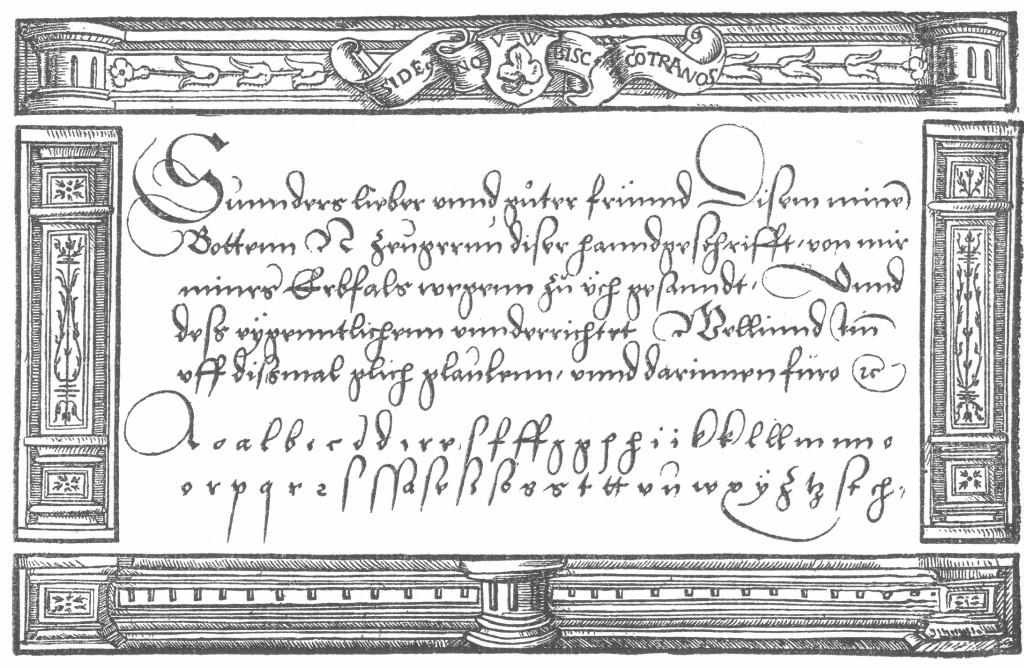
Grund für Blocksatz im Buchdruck
Ich wundere mich etwas, dass plötzlich pauschal über "alte Meister" und das Infragestellen (oder Nicht-Infragestellen) vermeintlich althergebrachter Regeln diskutiert wird. Ich habe nirgends die Forderung gelesen, den Blocksatz abzuschaffen, schon gar nicht vom Fragesteller, der ursprünglich nur wissen wollte, ob es  einen "historischen, technischen oder kaufmännischen Grund" für diese Tradition gibt - also Dinge jenseits ästhetischer Erwägungen.
Interessant ist in diesem Zusammenhang vielleicht ein Blick über den Tellerrand, in andere Schriftkulturen. Im Arabischen beispielsweise hat die Kalligraphie seit jeher einen besonders hohen Stellenwert und genießt als Kunstform höchste Wertschätzung, nicht zuletzt aus religiösen Gründen. Eine mit der europäischen vergleichbare, jahrhundertealte Tradition des Buchdrucks mit beweglichen Lettern gibt es nicht, auch gibt es keine so augenfällige Abgrenzung zwischen Druck- und Schreibschriften. Viel häufiger als bei uns wurde und wird Text kalligraphisch ausgeschmückt, eingerahmt, bildet eigene Formen und Ornamente oder sogar bildhafte Darstellungen.
Und eben auch bei Handschriften regelmäßig "Blocksatz" (iSv. bündigen Zeilenenden links). Das überrascht nicht, denn mit arabischen Schriftzeichen ist dies viel leichter zu erreichen als mit lateinischen Druckbuchstaben. So lassen sich viele Buchstaben in ihrer Weite ändern, mit den Verbindungen kann man sowieso spielen (da geht eine einzige schon mal über eine halbe Zeile), und je nach Schrift kann sogar innerhalb einer Zeile schräg geschachtelt oder "gestapelt" werden. Ich fand es bei Durchsicht einiger Beispiele jedenfalls bemerkenswert, wie stark und wie häufig auf bündige Textränder geachtet wird.
Es scheint also etwas dran zu sein, dass ein Text, dessen äußere Begrenzungen einheitlich sind, ganz grundsätzlich, und sogar unabhängig vom Schriftsystem, das Auge erfreut, als "wertiger", "schöner" und "erhabener" wahrgenommen wird. Dann wäre tatsächlich der ästhetische Aspekt ausschlaggebend - und damit nichts,  was man wissenschaftlich untermauern könnte. (Ebensowenig wie es ja auch noch nicht gelungen ist zu beweisen, dass der Goldene Schnitt ein universelles Gestaltungsgesetz sei, wie oft behauptet wird).
Bezieht sich das noch auf die arabischen Handschriften?
Diese mit lateinischen Druckschriften zu vergleichen ist etwas weit hergeholt. Das oben beschriebene ist aber durchaus auch mit unseren Handschriften möglich und wurde auch von europäischen Schreibmeistern praktiziert.
Das ist jetzt gerade mal ein Fundstück aus dem Netz. In diesem Buch hat der Autor aber viele Schreibmeisterblätter zusammengetragen, die ebenso spannend sind. Sicherlich hat die Kalligrafie im arabischen Raum ein anderen Stellenwert und eine ganz andere Entwicklung als bei uns, das heißt aber nicht, dass man mit unserer Schrift nicht so kreativ umgehen könnte oder es diese Tradition gar nicht gab.
Aber das geht ja auch wieder am Thema vorbei ...
Vergleichen kann man alles, Äpfel und Birnen sogar besonders gut ;-) Gefragt war ja nach Gründen für den Blocksatz beim Buchdruck. Von daher finde ich es interessant zu sehen, dass bündige Ränder auch in einem ganz anderen und vor allem viel stärker von handschriftlicher Kalligraphie (und eben nicht vom Buchdruck) geprägten Schriftsystem seit jeher als schön, wichtig und erstrebenswert erachtet werden.
Alles gut, da spricht ja gar nichts gegen …
Ich wollte nur darauf hinaus, dass das nichts originär arabisches ist, sondern, dass es mit (fast) jeder Handschrift geht und mitunter gemacht wurde. Mag sein, dass das im arabischen Raum besser und deutlicher zu sehen ist.
Viele Leute denken bei Kalligrafie sehr schnell an japanisch/chinesisch oder weisen auf die Verspieltheit und Stellung der arabischen Schriften hin, ohne zu bemerken welche Schätze auch die westliche Kalligrafie birgt. Das ist Alltag, wenn man mit dieser Kunst in die Öffentlichkeit geht und deswegen ist es fast schon Affekt von mir, darauf hinzuweisen
;-)
Hallo, ich bin auf diesen Thread gestossen, nachdem ich - der vor 20 Jahren Schriftsatz beruflich praktizierte - aktuell ein eigenes (Sach-) Buch setze. Mir erscheint der Flatter- genauer: Rauh-Satz als besser lesbar, daher habe ich den Entwurf so gesetzt, und dies mit Lektoren und Freunden diskutiert; und im Netz Diskussionen wie diese gelesen.
Ein wichtiges Argument für Rauhsatz vermisse ich in diesem Thread (oder habe es überlesen), weshalb ich mich anmeldete und den Thread nach einem Jahr noch einmal aufgreife.
Heute lesen wir zunehmend Texte im Netz im Flattersatz - aus einem einfachen Grund:
> Der Gestalter kennt, anders als bei Druckschriften, die "Seitengröße" des Lesers nicht, manche nutzen große Bildschirme, andere Laptops, Tablets oder Smartphones. Und welche Schriftgröße der einzelne dann bevorzugt (Altersweitsicht?), weiss er auch nicht.
Das hört sich für mich aber zumindest schon einmal nach einer Art »Gleichwertigkeit« beider Satzarten an. Wäre ja auch schon mal eine An- bzw. Aussage für diesen Strang. ;-)
Im Punkt der Unterscheidbarkeit der Seitenbilder gibt es »vielleicht« eine Gleichwertigkeit. Das sich daraus eine Gleichwertigkeit für den Einsatz in Büchern ergibt sehe ich nicht ...